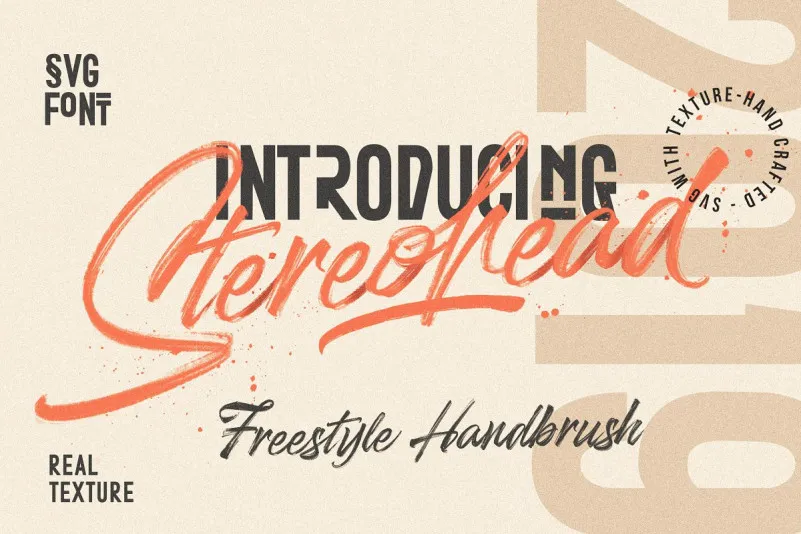
Stereohead Brush Font SVG – Download Grátis
Olha quem está aqui! Introduzimos a font Stereohead para vocês. Esta é uma font script bela e elegante, disponível tanto em SVG opentype quanto com extras adicionais. Foi criada como uma combinação de escrita manuscrita e estilo de desenho à mão. Ideal para projetos diversos como logo, design gráfico, produtos personalizados, embalagens, cartões de presentes e até mesmo para trabalhos nas redes sociais. Agora, vamos ao detalhe: Stereohead Brush Font SVG é uma font script estilizada com um aspecto verdadeiramente pintada à mão, fornecendo um look semelhante a um pincel seco. Isso o torna perfeito para aplicar em assinaturas, logotipos e até mesmo citações escritas a mão. Stereohead Brush Font SVG foi criado pelo Dirtyline Studio, uma equipe de profissionais que sempre busca manter os detalhes meticulosamente cuidados no design. Com esta font, você tem uma ótima maneira de inovar em sua arte digital e torná-la única e elegante. Seja para um projeto pessoal ou comercial, a Stereohead Brush Font SVG é uma escolha inteligente que certamente adicionará valor ao seu trabalho gráfico. Fique à vontade para explorar e descobrir todas as possibilidades criativas com esta font estilizada.